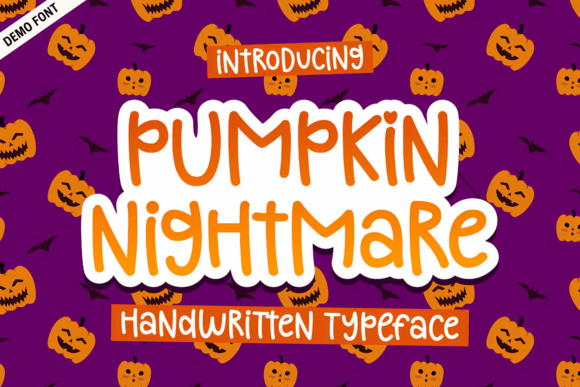
Pumpkin Nightmare Demo
การค้นหาองค์ประกอบการออกแบบที่เหมาะสมอาจเป็นเรื่องท้าทาย แต่ Pumpkin Nightmare Demo นำเสนอคอลเลกชันที่โดดเด่นซึ่งช่วยยกระดับงานของคุณได้ทันที
ไม่ว่าคุณจะสร้างผลิตภัณฑ์ POD (Print on Demand) คำเชิญงานแต่งงาน หรือกราฟิกโซเชียลมีเดีย Pumpkin Nightmare Demo ก็เหมาะสมอย่างยิ่ง